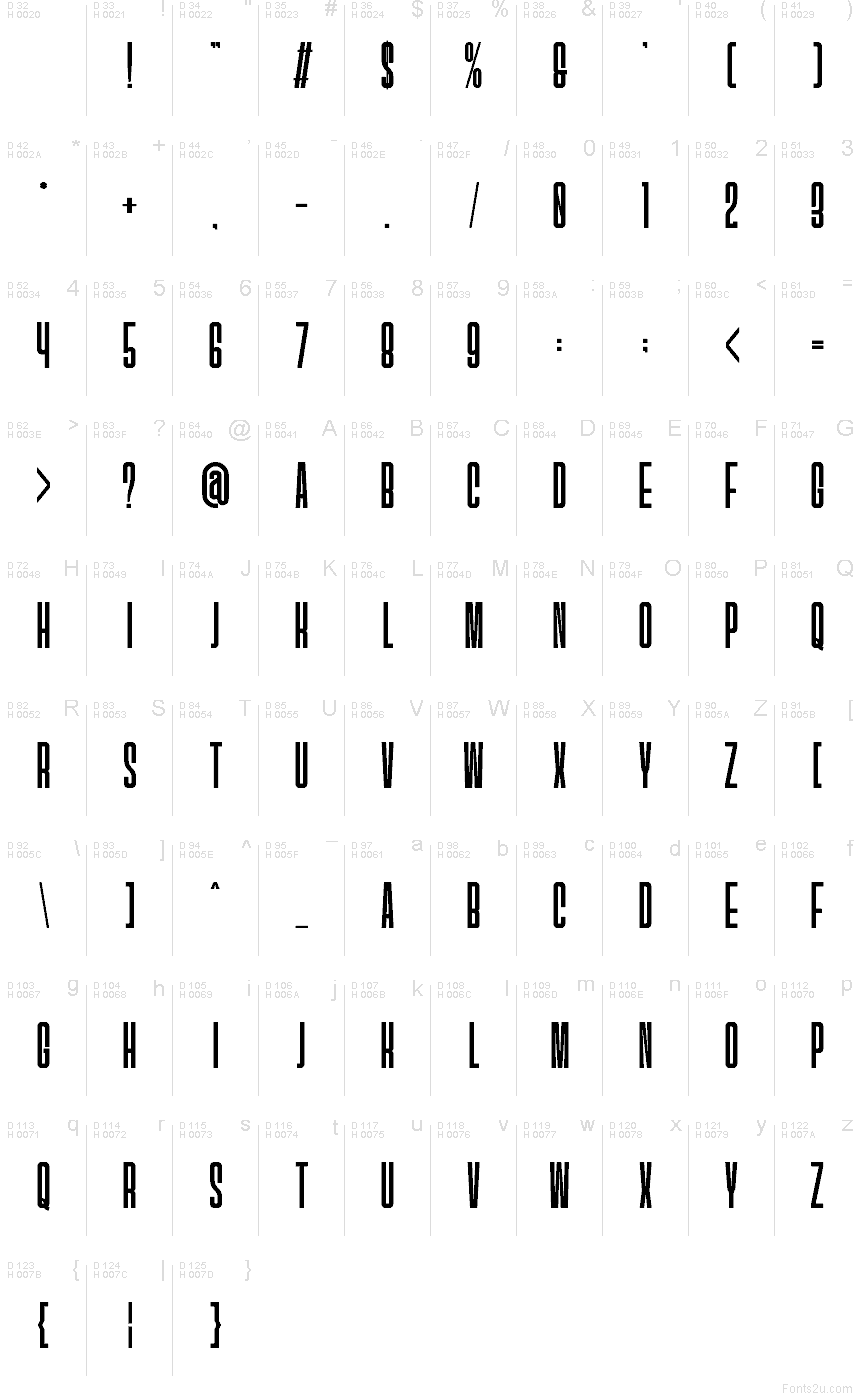
Degolan, de Ermedia Studio, es una tipografía sin remates ultracondensada y gratuita con letras imponentes y de trazado ceñido. Los marcados contrastes entre las amplias verticales y las uniones finas como un cabello confieren a las formas una nitidez dramática, similar a la del papel recortado. Sus proporciones estrechas crean una contundente pared tipográfica sin recurrir a ornamentos.
Un cartel de moda puede aprovechar esa silueta alargada como titular y como estructura gráfica, y esa misma severidad encaja en portadas de revistas y diseños para eventos musicales. Estas proporciones extremas pertenecen por naturaleza a la moda contemporánea y la cultura de club.